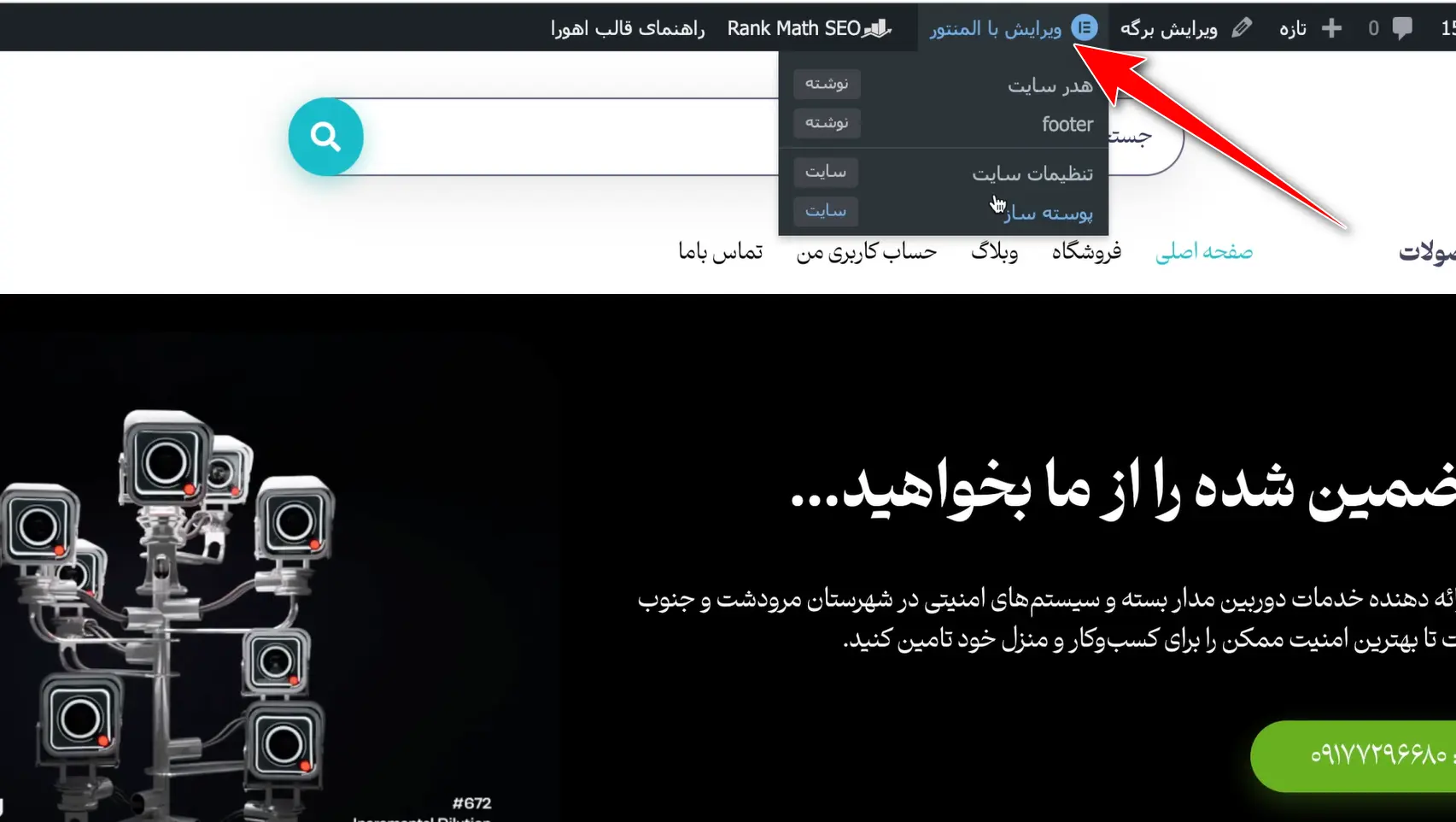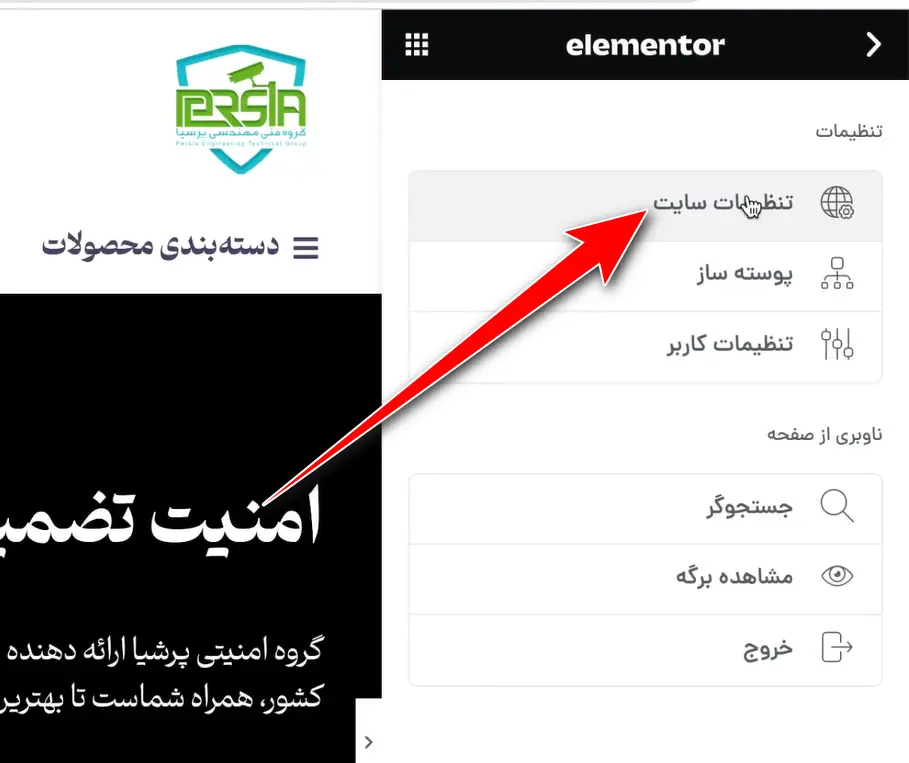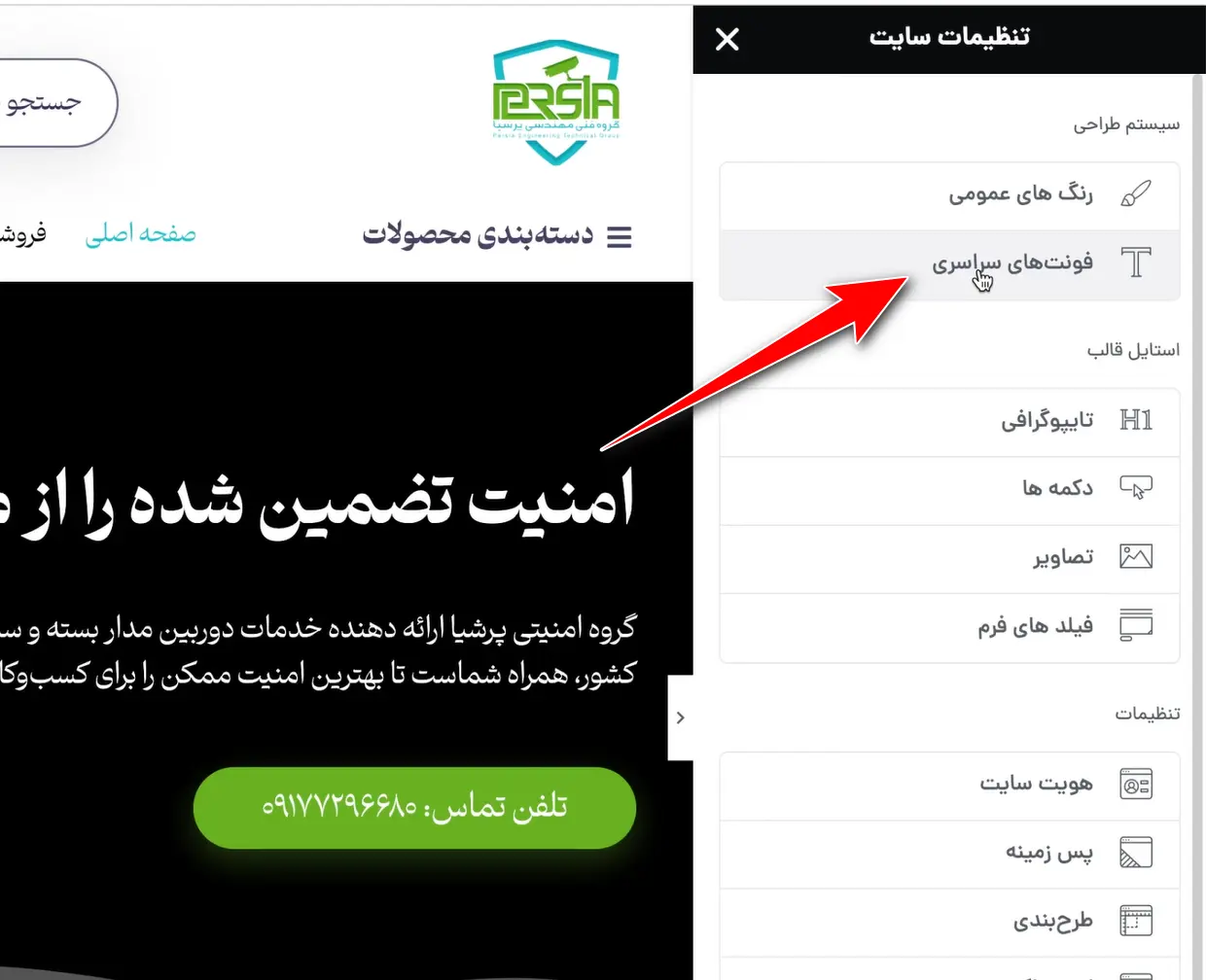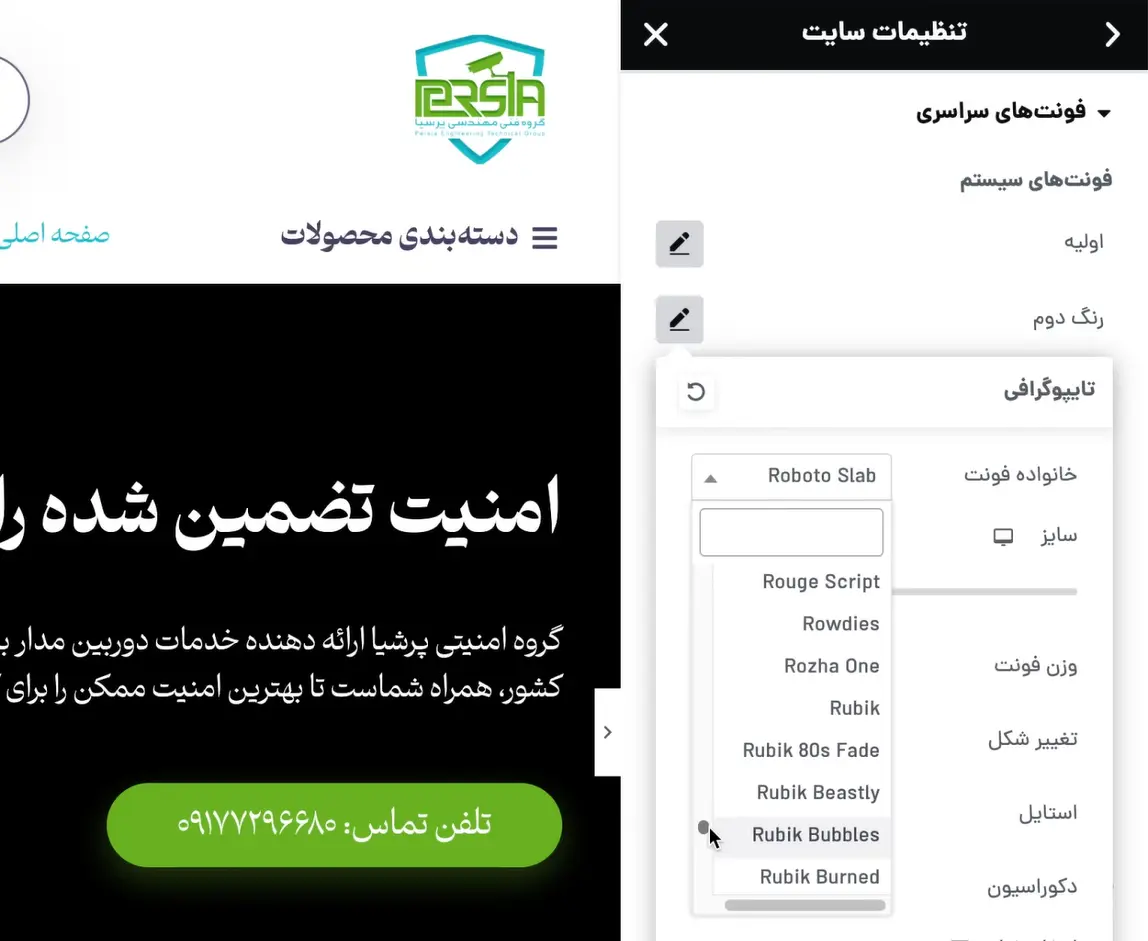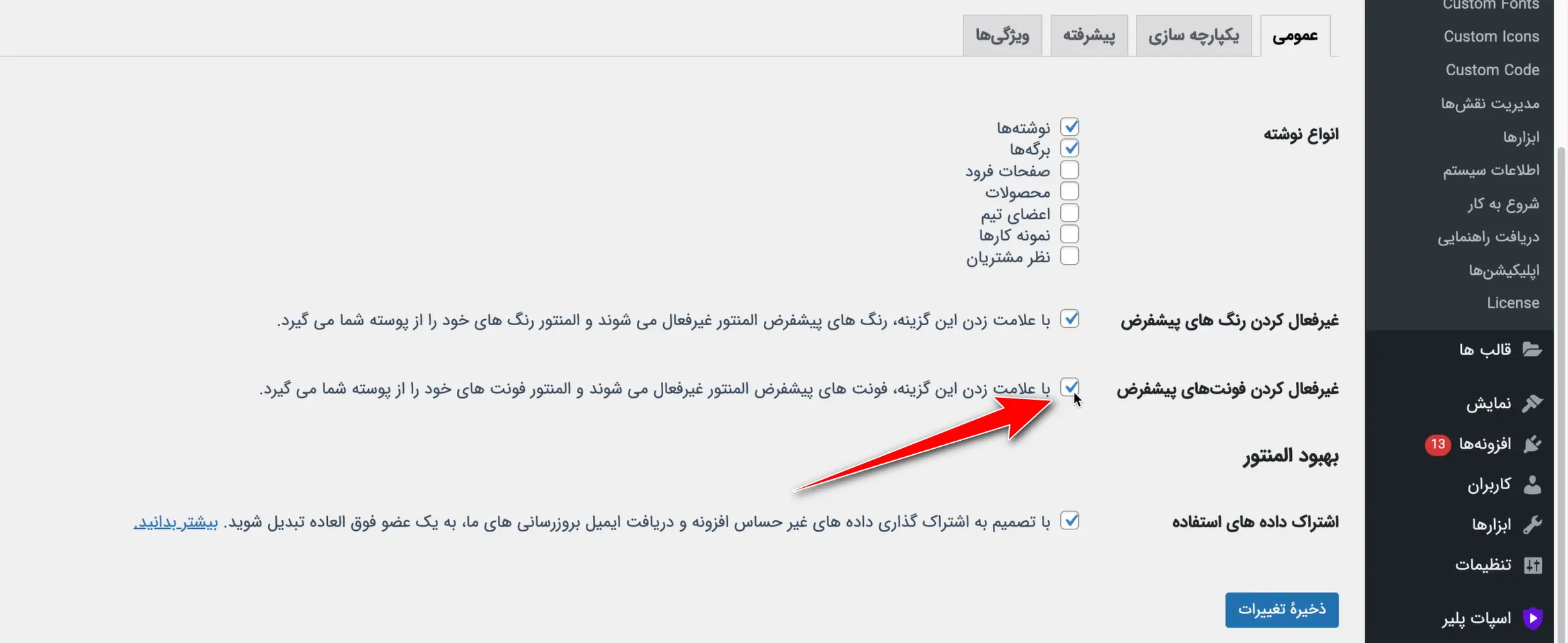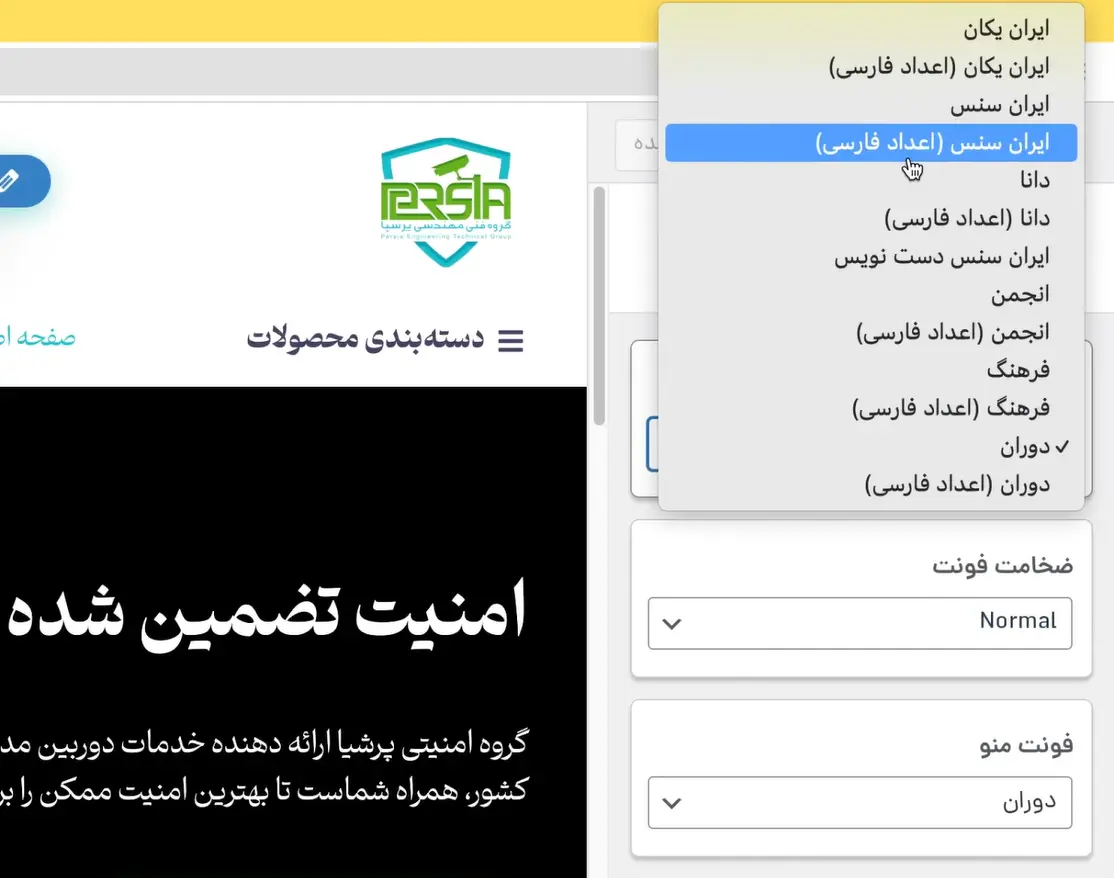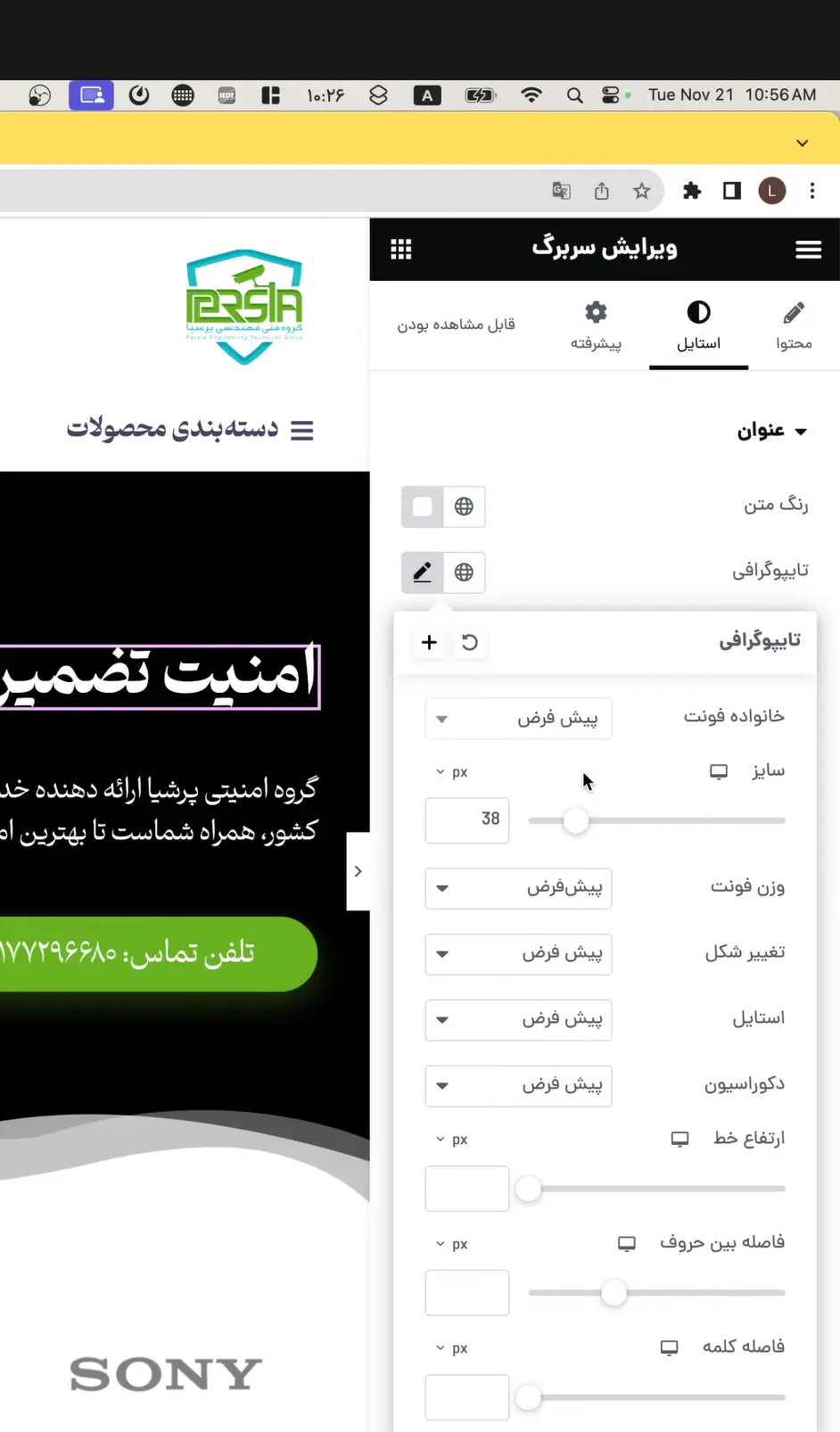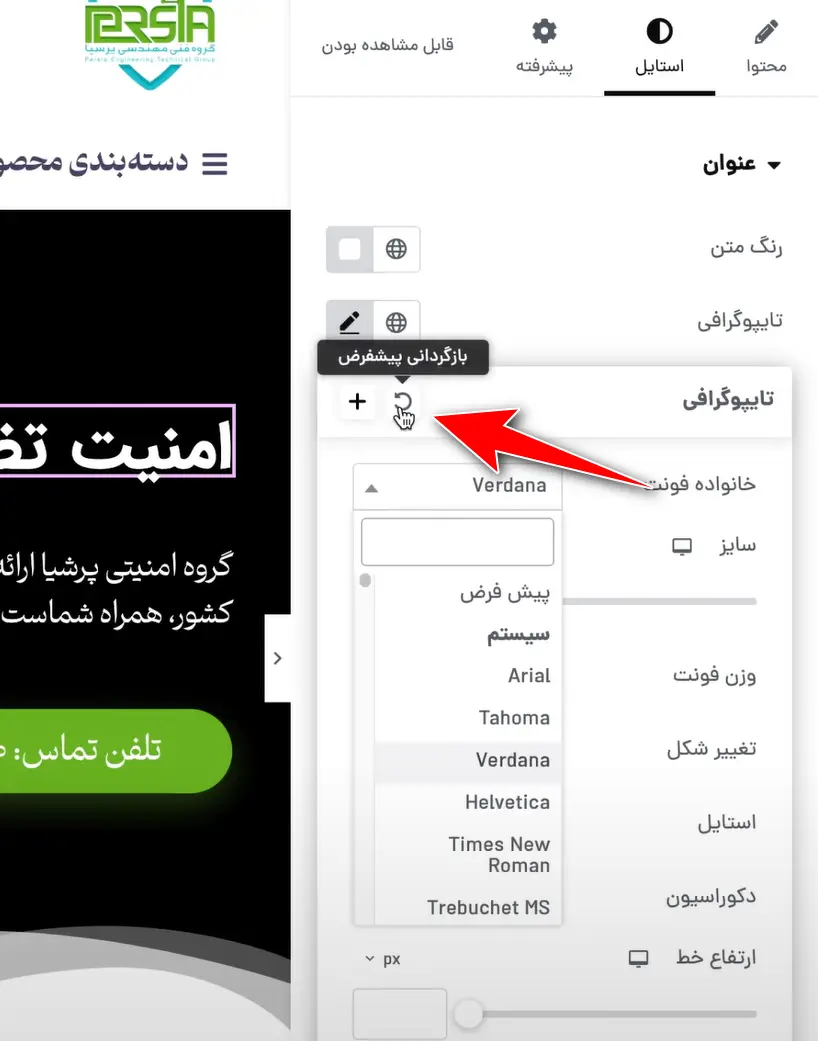
اضافه کردن فونت به المنتور و تغییر فونت در وردپرس
برای اضافه کردن فونت به المنتور باید ببینیم سایت ما فارسی هست یا انگلیسی. در سایت فارسی از قالب با فونت فارسی و در سایت انگلیسی از گوگل فونت استفاده می‌کنیم.
واقعاً یکی از اولین کارایی که موقع طراحی سایت با المنتور باید انجام بدیم، انتخاب فونت مناسب برای سایته. فونت فقط یه جزئیات کوچیک نیست؛ مستقیم روی حس‌وحال سایت، تجربه کاربر و حتی حرفه‌ای بودن ظاهر کلی سایت تأثیر داره. مهم نیست سایتت فروشگاهیه، شرکتیه یا شخصی، تو هر حال باید حواست به فونت باشه.
من همیشه توصیه می‌کنم قبل از اینکه وارد فاز طراحی بشی، اول تنظیمات پایه‌ای المنتور مثل رنگ‌بندی سراسری و مخصوصاً فونت سراسری رو انجام بدی. اتفاقاً یه مقاله‌ی جدا هم درباره‌ی تنظیم رنگ توی المنتور براتون نوشتم، اما اینجا قراره کامل درباره‌ی فونت صحبت کنیم.
پس بریم با هم ببینیم چطور می‌تونیم فونت‌های پیش‌فرض المنتور رو تغییر بدیم، فونت‌های فارسی رو بهش اضافه کنیم و کاری کنیم که از همون اول، سایت با فونت درست و حسابی نمایش داده بشه.
افزودن فونت به المنتور با توجه به زبان سایت
خب حالا بیایم سر اصل مطلب. کاری که قراره انجام بدیم، تغییر فونت سایته. ولی قبل از اینکه بریم سراغ ابزارها و تنظیمات المنتور، باید چندتا نکته‌ی مهم رو در نظر بگیریم، مخصوصاً درباره‌ی زبان سایت.
ببین، این خیلی مهمه که زبان سایتت فارسیه یا انگلیسی. چون فونتی که برای یه سایت فارسی خوبه، ممکنه اصلاً به درد یه سایت انگلیسی‌زبان نخوره و برعکس. یعنی انتخاب فونت باید بر اساس زبان و مخاطب سایتت باشه، نه فقط سلیقه‌ی شخصی.
مثلاً اگه سایتت قراره به زبان فارسی باشه و مخاطبای تو فارسی‌زبان هستن، خب طبیعتاً باید بری سراغ فونت‌های فارسی مثل «ایران‌سنس»، «وزیر»، «شبنم» یا حتی فونت‌های ساده‌تر مثل «Tahoma». این فونت‌ها برای متن فارسی طراحی شدن و هم از نظر ظاهر و هم از نظر خوانایی، خیلی بهتر جواب می‌دن.
برعکسش اگه سایتت انگلیسیه یا مثلاً واسه یه پروژه‌ی بین‌المللی طراحی می‌کنی، باید فونت‌هایی رو انتخاب کنی که مناسب متن انگلیسی باشن، مثل «Roboto»، «Open Sans»، یا «Lato».
پس قدم اول توی تغییر فونت اینه که دقیقاً بدونی قراره سایتت به چه زبانی باشه. از اونجا به بعد، انتخاب فونت مناسب خیلی راحت‌تر می‌شه و دیگه وسط طراحی، با مشکل نمایش یا به‌هم‌ریختگی فونت روبه‌رو نمی‌شی.
اگه زبان سایت انگلیسی بود چه کنیم؟
حالا فرض کنیم زبان سایتت انگلیسیه. اینجاست که یه امکان خیلی جذاب به کارت میاد به اسم Google Fonts. گوگل فونتس یه سرویس فوق‌العاده‌ست که کلی فونت رایگان و با کیفیت بالا در اختیارت می‌ذاره. هر فونتی که بخوای، فقط با چند کلیک می‌تونی به سایتت اضافه کنی و ازش استفاده کنی، اونم بدون نیاز به دانلود یا نصب جداگانه.
برای استفاده از فونت‌های گوگل تو المنتور، باید بری سراغ تنظیمات سایت. اگه تو پنل وردپرس هستی، می‌تونی از منوی المنتور وارد بخش تنظیمات بشی، ولی بهترین راهش اینه که وارد یکی از برگه‌های سایتت بشی، مثلاً صفحه اصلی، و بزنی روی “ویرایش با المنتور”.
بعد که المنتور باز شد، بالا سمت چپ یه آیکون سه‌خطی هست. اونو که بزنی، یه گزینه به اسم “تنظیمات سایت” ظاهر می‌شه.
وقتی وارد این بخش بشی، یه قسمت داریم به اسم فونت‌های سراسری که دقیقاً همین‌جاست که باید کارمون رو شروع کنیم.
توی این بخش می‌تونی مشخص کنی فونت اصلی سایت چی باشه، فونت دوم چی باشه، فونت‌های عنوان‌هات چی باشن و کلی گزینه دیگه. چون زبان سایتت انگلیسیه، فونت‌ها با پیش‌نمایش خودشون نشون داده می‌شن، یعنی همون لحظه می‌تونی ببینی که ظاهر هر فونت چطوریه. ولی اگه سایتت فارسی باشه، این پیش‌نمایش به‌درستی نشون داده نمی‌شه چون گوگل فونت‌ها روی متن فارسی درست رندر نمی‌شن.
انتخاب یکی از فونت‌های گوگل
برای سایت‌های انگلیسی، فونت‌هایی مثل Roboto، Open Sans، یا Lato از بهترین گزینه‌ها هستن. مخصوصاً Roboto که هم خوانایی بالایی داره، هم ظاهر شیکی داره، هم برای موبایل و دسکتاپ خوب جواب می‌ده.
اگه بخوای ظاهر سایتت یکم متفاوت‌تر و خاص‌تر بشه، می‌تونی فونت‌هایی مثل Raleway یا Montserrat رو هم امتحان کنی. اینا فونت‌های مدرن و شیک‌تری هستن. و اگه دنبال یه فونت فانتزی یا خاص باشی، Google Fonts کلی گزینه برات داره.
البته فراموش نکن که فونت فقط توی تنظیمات سراسری تغییر نمی‌کنه؛ هر وقت داشتی یه المان خاص مثل عنوان، متن یا دکمه رو ویرایش می‌کردی، می‌تونی بری تو تب Style و فونت همون بخش خاص رو جدا تنظیم کنی. ولی پیشنهاد من همیشه اینه که اول فونت سراسری رو ست کنی، بعد اگه خواستی برای بخش خاصی فونت متفاوت بزاری.
اگه زبان سایت فارسی بود چه کنیم؟
اما خب موضوع اصلی ما اینجاست که اکثر ما داریم سایت فارسی‌زبان طراحی می‌کنیم. پس اون چیزی که تا الان درباره‌ی گوگل فونتس گفتیم، بیشتر به درد سایت‌های انگلیسی می‌خوره. اگه سایتت فارسیه، قضیه یه‌کم فرق می‌کنه. تو ایران، به‌خاطر اون سرعت اینترنت بی‌نظیری که همه‌مون تجربه‌ش کردیم، خیلی از فونت‌های گوگل یا اصلاً لود نمی‌شن، یا اگه بشن، با سرعت خیلی پایین لود می‌شن. نتیجه‌شم واضحه که سرعت لود سایت پایین میاد و تجربه‌ی کاربر هم خراب می‌شه.
مرحله اول: غیرفعال کردن فونت‌های گوگل از المنتور
برای همین، اگه سایتت فارسیه، مرحله‌ی اولی که باید انجام بدی اینه که کل فونت‌های گوگل رو توی تنظیمات المنتور غیرفعال کنی. چون این فونت‌ها از سرورهای گوگل بارگذاری می‌شن و به‌دلیل تحریم‌ها و محدودیت‌های اینترنت ایران، اصلاً گزینه‌ی مناسبی برای ما نیستن.
پس اگه تا اینجا توی تنظیمات سایت المنتور رفتی و تغییراتی زدی، ولی زبان سایتت فارسیه، حتماً اون تغییرات رو ذخیره نکن. بهتره از فونت‌هایی استفاده کنیم که به‌صورت لوکال (یعنی روی خود هاست سایت) بارگذاری می‌شن و مخصوص زبان فارسی طراحی شدن. هم ظاهر سایت رو زیباتر می‌کنن، هم خیلی سریع‌تر بارگذاری می‌شن و از نظر سئو هم خیلی بهترن.